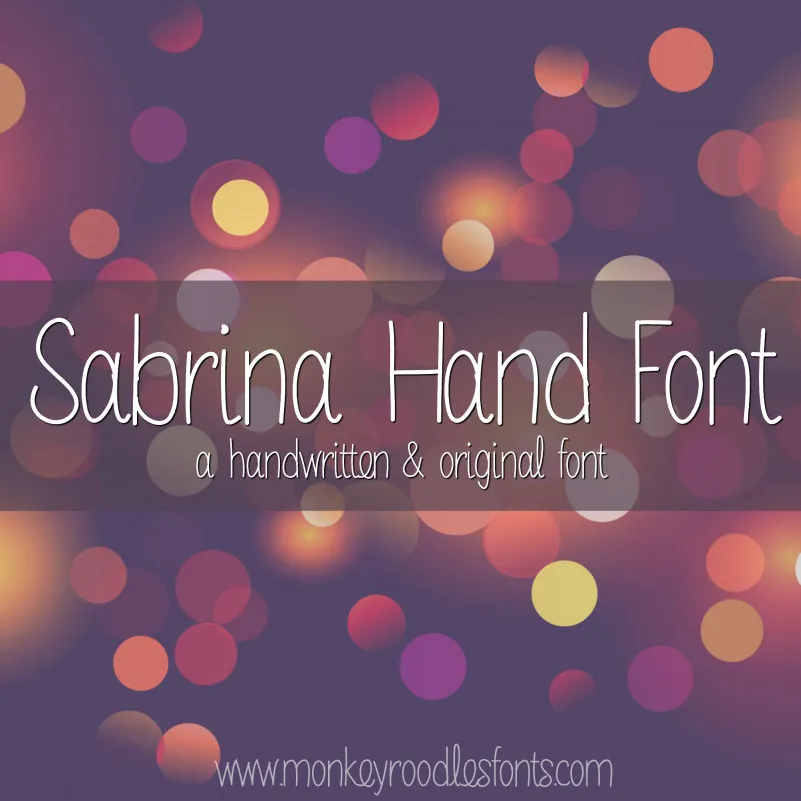
MRF Sabrina Hand Font – Download Grátis
A MRF Sabrina Hand Font é uma elegante escrita a mão, projetada por Hamilton. Suave e envolvente, ela combina perfeitamente com qualquer projeto pessoal ou artes gráficas de hobby. Perfeita para criações de calendários, presentes personalizados, design de logotipos ou até mesmo como uma fonte de escrita digital em blogs e sites pessoais. Com seu charme natural e sua caligrafia agradável ao olho, a Sabrina Hand é ideal tanto para aqueles que buscam um toque delicado quanto para quem deseja algo mais elaborado em seus trabalhos. Sua versão livre de compra está disponível para uso pessoal; se quiser incorporá-la em projetos comerciais, por favor, consulte as condições de licenciamento no website oficial da font designer. Visite www.monkeyroodlesfonts.com para obter mais informações e achar seu novo favoite em fontes a mão.